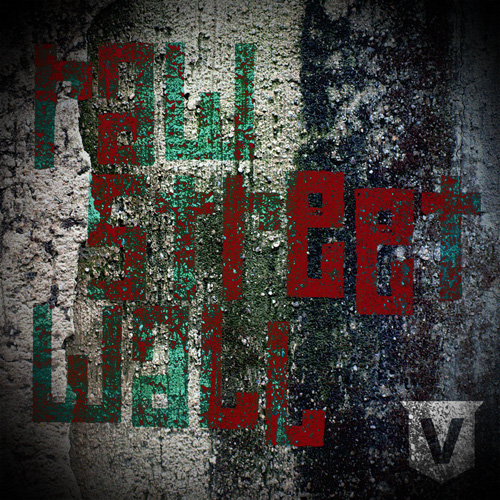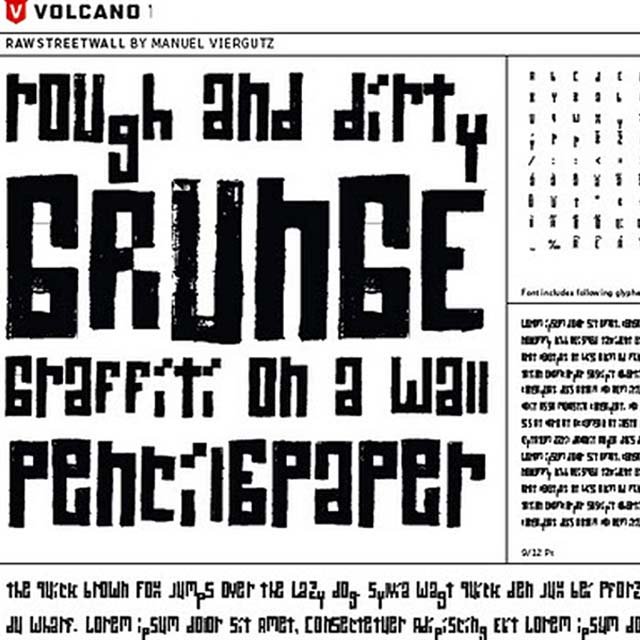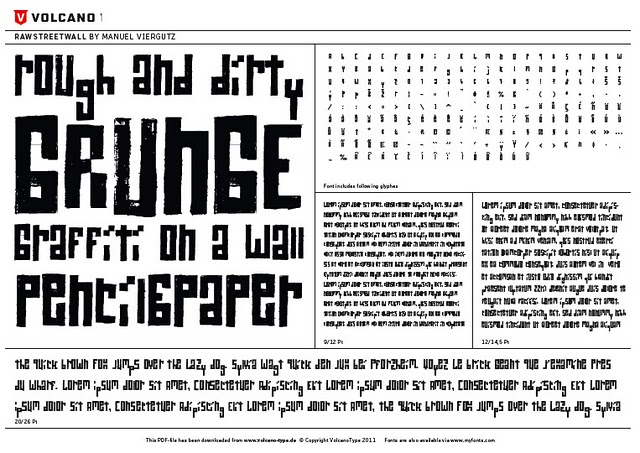
RAWSTREETWALL ist eine grobe, dreckige und hässliche Schrift. Der letzte Abschaum, direkt aus dem dunkelsten, stinkenden Hinterhof herausgekrochen, ein Albtraum, nichts für schwache Nerven. Und genau deswegen macht es auch unglaublich viel Spaß, mit ihr zu arbeiten! Sie spiegelt den Charakter von alten, verratzten Graffitis wider, hat aber auch etwas von Streetart-Elementen. RAWSTREETWALL beinhaltet einige Extrazeichen und Ligaturen, damit man damit auch schön spielen kann.
The Typeface "RawStreetWall" is created analogous. Traditionally with pencil and paper. So a hand-made typeface. "RawStreetWall" is a rough & dirty Grunge-Font for Headlines. Looks like Streetart or Graffiti on a wall. With alternative letters and ligatures.
RawStreetWall von Manuel Viergutz